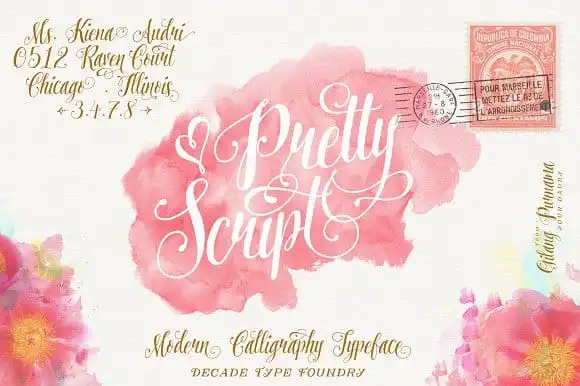
Pretty Script Font – Download Grátis
Introduzimos a ‘Pretty Script Font’, uma família de fontes com traços elegantes que trazem um toque romântico ao moderno. Essa família de fontes é perfeitamente adequada para aplicação em logomarcas, sacolas de viagem, cartões de aniversário e até mesmo design de casamento. A ‘Pretty Script Font’ é uma fonte script sofisticada que tem um toque encantador ao combinar com outras fontes. Além disso, a família vem equipada com ligaturas e alternativas para completá-la e dar-lhe um estilo único. Este conjunto de recursos torna a ‘Pretty Script Font’ perfeita para designers digitais à procura de uma fonte que seja tanto elegante quanto versátil. Seja você criando elementos de marca, personalizando sacolas de viagem ou trabalhando em design de casamento, a ‘Pretty Script Font’ está preparada para satisfazer suas necessidades. A ‘Pretty Script Font’ é um dos exemplos perfeitos de uma fonte script que combina sofisticação com encanto romântico, fazendo-a uma opção ideal para designers buscando trazer um toque especial a seus projetos. Escolha uma ou várias fontes da família e transforme suas ideias em realidade com esta fonte elegante e versátil.